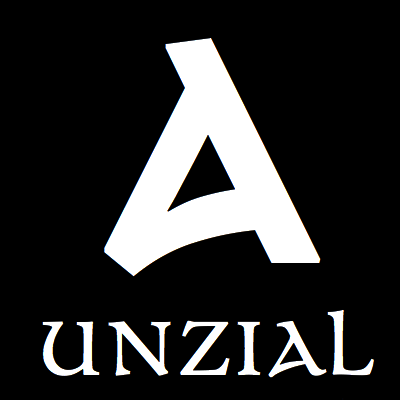
Die Popelka ist ein Unzial-Font, den Andreas Stötzner nach dem Vorbild des Vorspannes des Filmes »Drei Haselnüsse für Aschenbrödel« digitalisiert hat. Der tschechische Name dieses Filmes (deutsch-tschechische Koproduktion, 1973) ist »Tři oříšky pro Popelku«. Der Name des Fonts hat MyFonts am 30. Dezember 2016 veranlaßt, die Schrift vom Verkauf auszuschließen, da die Firma Berthold Direct Corp. (Chicago) ihre Rechte an dem Markennamen »Poppl« verletzt sah. Andreas Stötzner hat gegen diese Entscheidung Widerspruch eingelegt.
Schriftmuster der Popelka
Aus dem Vorspann von Drei Haselnüsse für Aschenbrödel